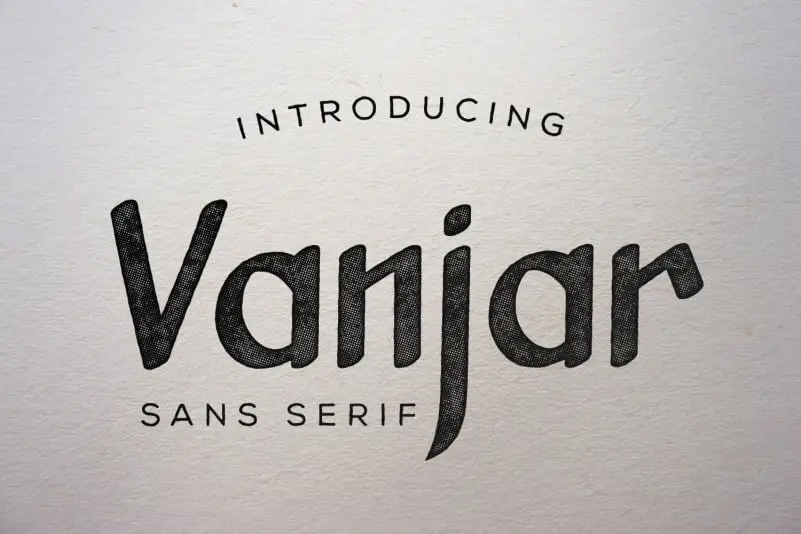
Vanjar Sans Serif Font – Fonte Grátis
Vanjar Sans Serif Font
A Vanjar Sans Serif Font é uma escolha versátil para aqueles que buscam uma tipografia moderna e elegante sem perder a utilidade. Com seu olhar contemporâneo, esta fonte se apresenta clara e sofisticada, adaptando-se de maneira incrível tanto em grandes tamanhos quanto em detalhes finos. Seu design permite que seja facilmente leitura, tornando-a excelente para aplicações variadas como headlines, corpos de texto, outdoors, ilustrações digitais e muito mais. Com uma estrutura pura e elegante, Vanjar é perfeitamente projetada para destacar em ambientes digitais ou físicos. Suas linhas leves e clean se adaptam a qualquer aplicação visual, fazendo-a adequada tanto para o layout da web quanto para criações gráficas offline. Não espere encontrar uma fonte tão versátil e sofisticada como a Vanjar Sans Serif Font em seu portfólio. Ela é um ótimo complemento para os designers que buscam transmitir elegância e modernidade de maneira clara e eficaz em seus projetos.